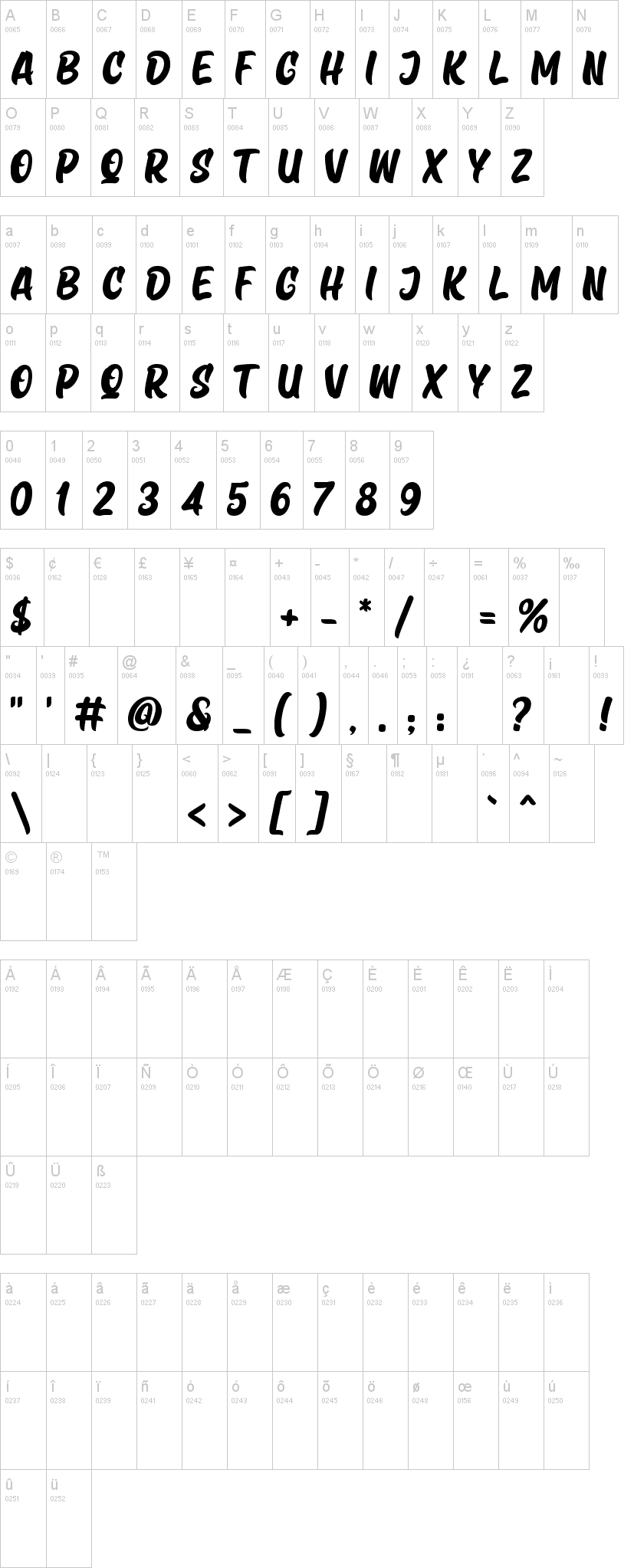
? Osaka Chips 字体是一款由日本设计师Hiroshi Osaka创作的欧美风格的字体,它有着清新的外观,清晰的结构,清晰的线条,细腻的细节,更加精致,更加简洁。它适合用于多种类型的项目,特别适用于标题,标语,招牌等,是一款让人印象深刻的字体。内容介绍
Osaka Chips是一款非常不错的手写艺术字体,具有很好的视觉感,适合于文化类的宣传设计、商业类品牌的广告和产品包装设计以及个性化文字排版等较多场景。